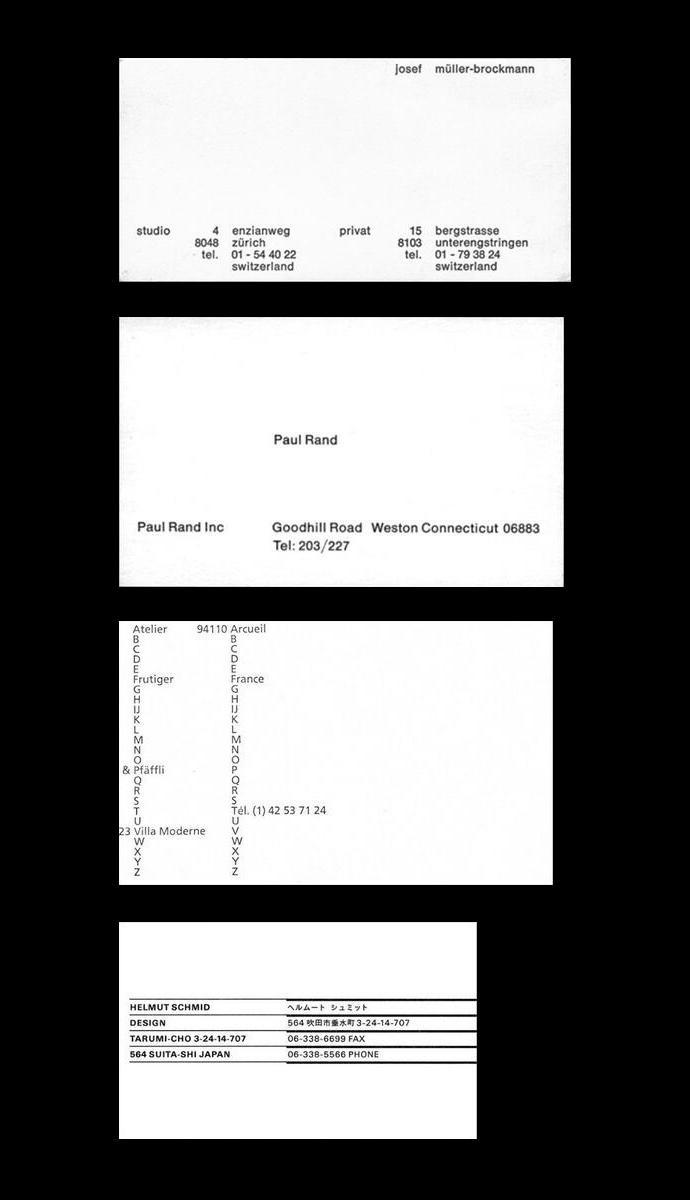
Die Müller-Brockmann-Visitenkarte ist wirklich ein Kleinod typografischer Gestaltung.
In der Tat.
Im Ernst: die Visitenkarte zeugt für mich von hoher typografischer Qualität. Das fängt bei der Wahl des 2:1-Formats an (viel schöner als das gebräuchliche von 85×55 mm) bis hin zur typografischen Inszenierung der Kontaktdaten. An der Visitenkarte wirkt nichts willkürlich oder dem Zufall überlassen. Natürlich steckt da auch ein gewisser typografischer Dogmatismus drin, der sich zugleich wie ein roter Faden durch das Schaffen Müller-Brockmanns zog.
Ja, wie er die Adressen gelöst hat, finde ich unaufgeregt aufregend. Und wie nahe am Rand er mit seinem Namen arbeitet… Alles wunderbar arrangiert und dem Weißraum Platz geschenkt.
Das ungewöhnliche Format würde mich interessieren. Das Seitenverhältnis entspricht nicht exakt 2:1, glaube ich. Wenn man davon ausgeht, dass Rand 85 x 50 mm gewählt hat, so entspräche die Karte von JMB 86 x 42 mm.
Edit: Da ich davon ausgehe, dass die Karten zusammengestückelt wurden, bleiben die Maße / ihr Größenverhältnis zueinander natürlich reine Spekulation…
Zum Vergleich auch die Visitenkarten von Adrian Frutiger und Helmut Schmid. Ich vermute, die Karte von Frutiger wurde durch eine Bildbearbeitung (?) links zu knapp beschnitten.
Mich stört an der Müller-Brockmann-Karte, dass zusammengehörende Daten in der zugrundeliegenden unsichtbaren Tabelle durch die Verteilung in unterschiedliche Spalten auseinandergerissen werden. Bei Telefon steht die Kategorie »tel.« in der linken und die eigentliche Angabe, also die Nummer, in der rechten Spalte. Bei  Hausnummer und Straße bzw. Postleitzahl und Ort müsste man eigentlich genauso verfahren. Hausnummer und Postleitzahl sind schließlich keine Kategoriebezeichnung wie »tel.«, sondern Teil der eigentlichen Information. Und Vorname und Nachname durch Tabulator und daraus resultierenden viel zu großen Wortabstand zu trennen finde ich nur noch absurd.
Die Paul-Rand-Karte ist da schon erheblich besser. Die finde ich auch gelungen und es stört mich eigentlich nur ein Detail, nämlich die Inkonsistenz mit dem Doppelpunkt hinter »Tel«. Wenn man schon auf den Punkt hinter der Abkürzung verzichtet (ich weiß nicht, ob das in Amerika üblich ist), dann sollte der Doppelpunkt doch erst recht entbehrlich sein.
Soweit die reine Lehre. Wenn man es wirklich so richtig richtig machen will, dann ist das sicherlich der bessere Weg. Ich habe jedenfalls keinerlei Schwierigkeiten, die Angaben auf der Visitenkarte zu lesen. Der Aufbau weckt mein Interesse und sticht angenehm aus dem Einheitsbrei von Visitenkartengestaltungen heraus.
Stellt sich aber schon die Frage ob eine "Inszenierung" ausgerechnet von Kontaktdaten tatsächlich von "typografischer Qualität" zeugt.
Läse ich da nicht Müller-Brockmann sondern einen NoName, ich fürchte ich würde das als "irgendwie originell sein wollen" (mit Betonung auf "wollen") einordnen.
Verstehe den Einwand eigentlich nicht. Kann man etwa irgendeine Angabe auf der Karte nicht sofort zuordnen? Eben. Und die Telefonnummern stehen nicht links in der Ziffernspalte, weil sie sonst deren Breite und somit die Gesamtbreite sprengen würden…
Welche Lehre? Karel Martens hat mir mal gesagt »In Typography, everything is possible as long it makes sense.«
Und wenn man ohne Not Vorname und Nachname dermaßen auseinanderreißt oder für Kategorie und Information auf kleinstem Raum eine uneinheitliche Spaltenzuordnung vornimmt, dann ergibt das für mich eben keinen Sinn. Das hat nichts damit zu tun, dass man die Angaben auf der Karte nicht zuordnen könnte (auch wenn die Platzierung der Hausnummer vor der Straße ein unnötiger Stolperstein ist).